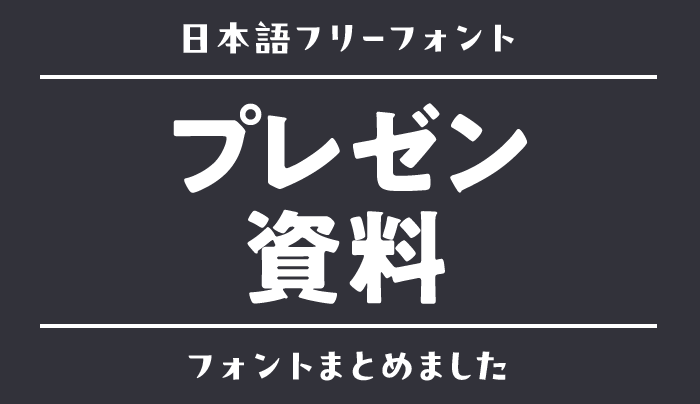
「プレゼン資料」にぴったりな日本語フリーフォント15選
伝わるプレゼン資料では、文字の見た目だけでなく、情報の役割が整理されています。結論を示す見出し、内容を説明する本文、図表の補足。同じ書体でも太さと大きさを変えるだけで、読み手の視線を案内できます。
今回は、フォントラボからプレゼン資料に使いたいフォントを紹介します。本文向けのゴシック、親しみを添える丸ゴシック、強調や引用に使う書体を選びました。15種類を一つの資料で使うのではなく、基本の1書体と必要なアクセントを選ぶための候補集です。
プレゼン資料で役割別に選ぶ日本語フリーフォント
Noto Sans
おすすめの場面企画書の本文/図表のラベル/社内説明スライド
まず基準にしたい、クセの少ないゴシック。
日本語資料ではNoto Sans JPなど日本語対応のものを選びます。字形に強い演出がなく、数字や文章を整理して見せたい場面に使いやすい書体です。まず本文をこの書体で揃え、見出しだけ太くすると資料の軸が決まります。どの用途にも万能と考えず、投影時には注記の大きさや漢字のつぶれを確認しましょう。
LINE Seed JP
おすすめの場面サービス紹介/採用説明/社外向けの提案資料
親しみと明快さを、同じ資料で両立。
角に丸みを持つゴシックで、堅苦しくしすぎず情報を伝えたいときに向いています。初めてサービスに触れる人への説明や、採用説明会の資料にもおすすめ。複数の太さを使い、見出しと本文の役割を作れます。親しみを出すために装飾を足す前に、書体だけで印象が整うか試してみてください。
梅M+ゴシック
おすすめの場面配布用の企画書/文章中心の報告書/補足資料
端正な文字で、説明をすっきり読ませる。
梅ゴシックにM+を組み合わせた書体で、整った印象の文章を作りたいときの候補です。細めの表情を活かし、手元で読める配布資料や補足ページに向いています。大きな会場での投影には、見え方を十分に確認してください。細い文字に情報を詰め込むより、段落を短くするほうが読みやすくなります。
Rounded M+
おすすめの場面研修スライド/利用者向け説明/教育サービスの提案
丸さを調整して、聞き手に合う距離感に。
角の丸め方に選択肢があり、資料の雰囲気に合わせやすい書体です。子ども向けの説明なら丸さを出し、一般向けの提案なら控えめにするなど使い分けられます。本文と見出しの太さも揃えて設計すると、やさしさだけに頼らない整理された資料に。長い文章はスライドに詰めず、要点を分けましょう。
小杉丸(Kosugi Maru)
おすすめの場面操作手順の説明/地域向けの案内/少人数の勉強会
すっきりした丸ゴシックで、説明を身近に。
曲線が素直で、親しみのある説明資料を作りたいときに向いています。操作の手順や、専門知識のない人に向けた案内におすすめ。見出しの差は無理な太字加工だけに頼らず、サイズや余白でも作れます。小さい画面で見る資料では、図中のラベルが細くなりすぎないよう確認してください。
源泉丸ゴシック
おすすめの場面サービスの導入案内/社内共有資料/お客様向け説明
やわらかすぎない丸みで、ビジネスの本文にも。
角を丸めながらゴシックの整った骨格を残しているため、説明を穏やかに見せたい場面に向きます。丸ゴシックを使いたいけれど、幼い印象は避けたいときの候補です。サービス導入の流れなど、複数ページにまたがる本文を揃える使い方がおすすめ。装飾的な強調は控え、図と文章の関係を明確にしましょう。
源柔ゴシック
おすすめの場面研修資料/提案書の本文/見出しと図表の統一
丸さと太さを選んで、資料全体を設計。
源ノ角ゴシックをもとにした、角丸の強さと太さに選択肢がある書体です。表紙から本文、図表まで同じ方向性で揃えたいときにおすすめ。細いウェイトは手元で読む用途、しっかりしたウェイトは投影用など、表示条件で選び分けられます。丸さをページごとに変えず、資料内で統一すると安定します。
和田研細丸ゴシック
おすすめの場面配布用の補足資料/落ち着いた表紙/短い引用文
細い文字は、手元で読む場面の選択肢に。
軽やかな丸ゴシックで、余白を多く取った資料に静かな印象を添えられます。一方で、極細の線は投影環境では弱く見えることがあるため、大会場の本文用としては慎重に選びたい書体です。十分なサイズの短い言葉や、手元で読む紙面から試すのがおすすめ。背景とのコントラストを確保しましょう。
源暎Nuゴシック
おすすめの場面結論を示す見出し/成果の強調/一言で伝えるスライド
太いゴシックで、結論の場所を明確に。
しっかりした太さにやわらかさがあり、スライドで最初に見てほしい言葉を示すのに向いています。説明文全体を太くするのではなく、結論や重要な数値の周辺に絞って使うのがおすすめ。標準的な本文書体と組み合わせれば、視線の順序を作れます。漢字が続く場合は詰まり具合を確認してください。
源暎きわみゴ
おすすめの場面新企画のタイトル/比較の結論/発表の章扉
重心の低い太字で、主張をしっかり支える。
太い画線と落ち着いた骨格が、短い見出しに安定感を与えます。提案の核心を一行で示すページや、章の切り替えにおすすめ。強調用の文字が増えると何が重要か分かりにくくなるので、一枚の中で主役を絞りましょう。数行の説明や図表の細かいラベルには、軽めの書体を組み合わせると整理できます。
モボ
おすすめの場面採用プレゼン/事業紹介/親しみのある提案書
角丸の表情で、堅さを少し和らげる。
モダンな骨格を持ちつつ、角の処理にやわらかさがあるゴシックです。企業の説明でも無機質にしたくないときや、人物写真を多く使う採用資料におすすめ。複数の太さで見出しと本文を揃えられます。少しレトロな表情もあるため、最先端の精密さを強調する資料では内容との相性を比べて選びましょう。
ぼくたちのゴシック
おすすめの場面新入社員向け研修/地域の説明会/利用方法の案内
かなのやさしさで、説明を受け取りやすく。
一般的なゴシックより、かなに親しみのある表情が感じられます。専門的な内容を初めて聞く人へ、落ち着いた口調で説明したい場面におすすめ。本文を長く詰め込まず、箇条書きや図と組み合わせると持ち味を活かせます。シリーズには別の書体もあるので、使用する版を資料内で揃えましょう。
いろは角クラシック
おすすめの場面文化事業の提案/地域の企画書/出版に関する発表